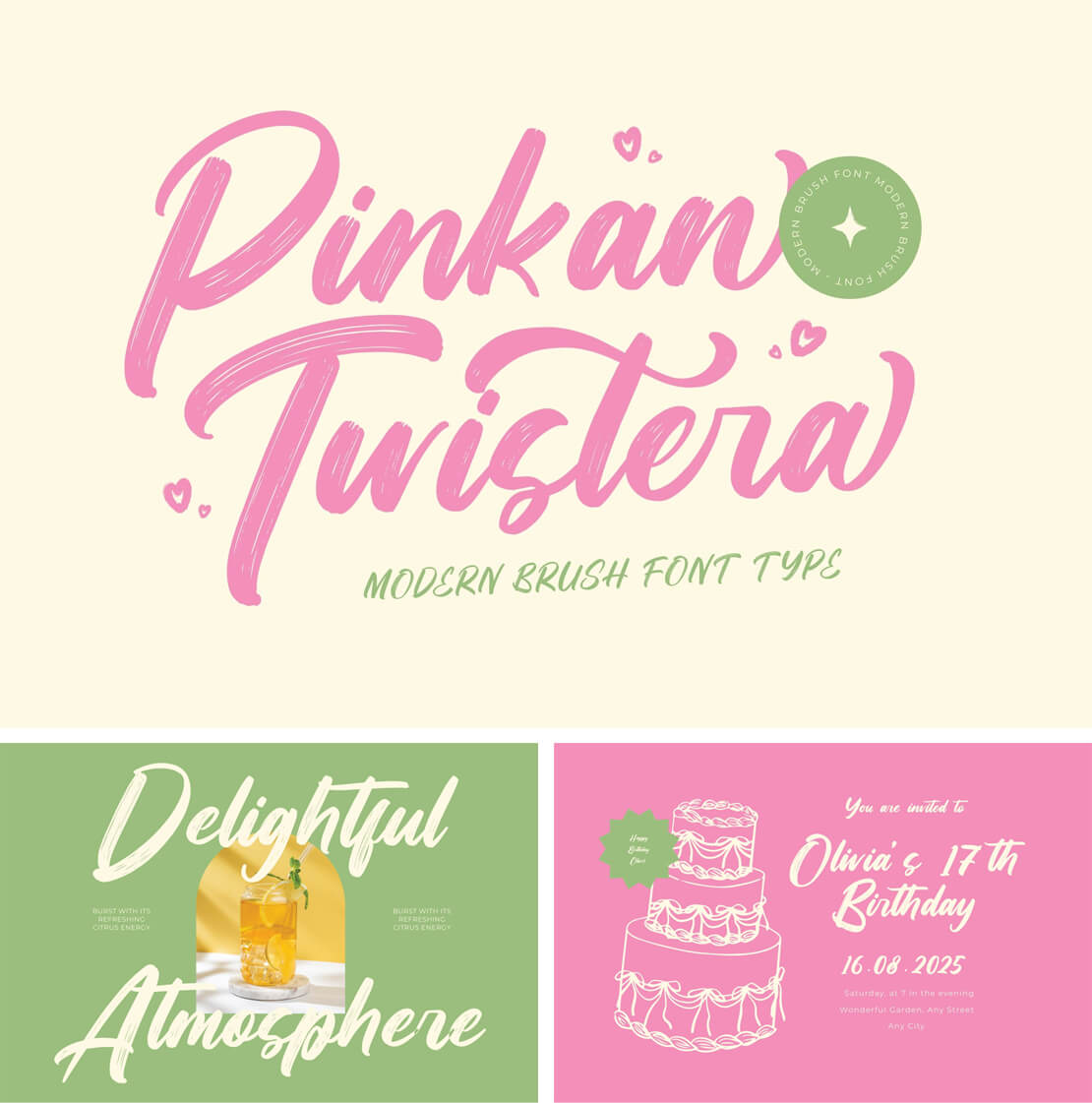
Pinkan Twistera
Die Brush-Schrift bietet einen handgemachten Pinsel-Charakter mit schwungvoller Linienführung. »Pinkan Twistera« steht kostenlos zum Herunterladen im Opentype- und TTF-Format sowie als Webfont bereit.